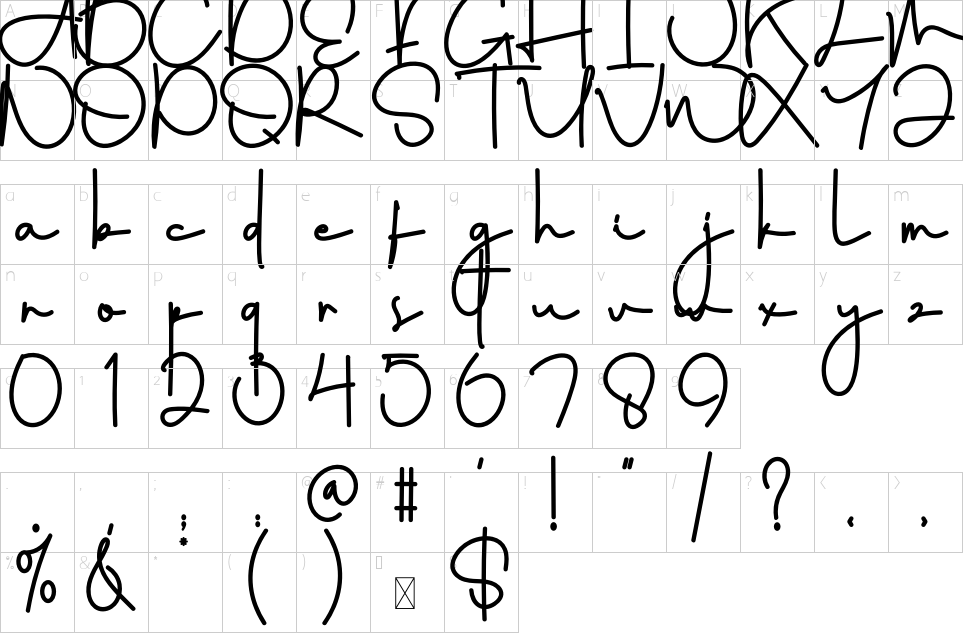
Autography Font – Fonte Grátis
Autography Font
Descubra a autêntica essência da escrita com o Autography Font. Este novo ícone da categoria de fontes gratuitas foi projetado por scratchones, oferecendo uma experiência de escrita única e versátil. Seu design fluido e sofisticado é perfeito para estilos de escrita modernos, tornando o Autography Font uma escolha irresistível para designers e amantes da escrita em geral. Com um download que já superou os 152 vezes, é evidente que o Autography Font está ganhando uma ampla aceitação por seus atributos incríveis. Que tal explorar o poder deste design único?